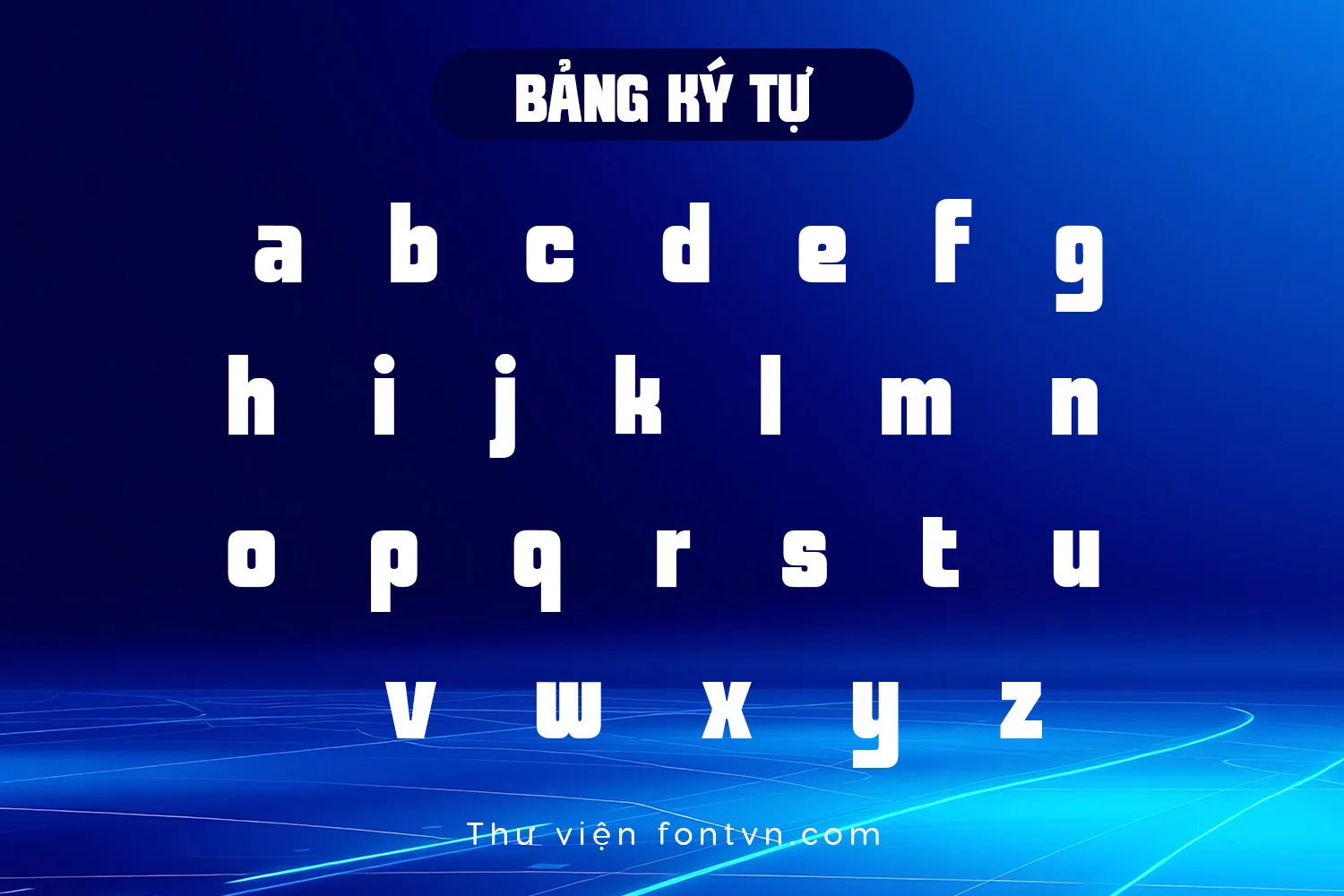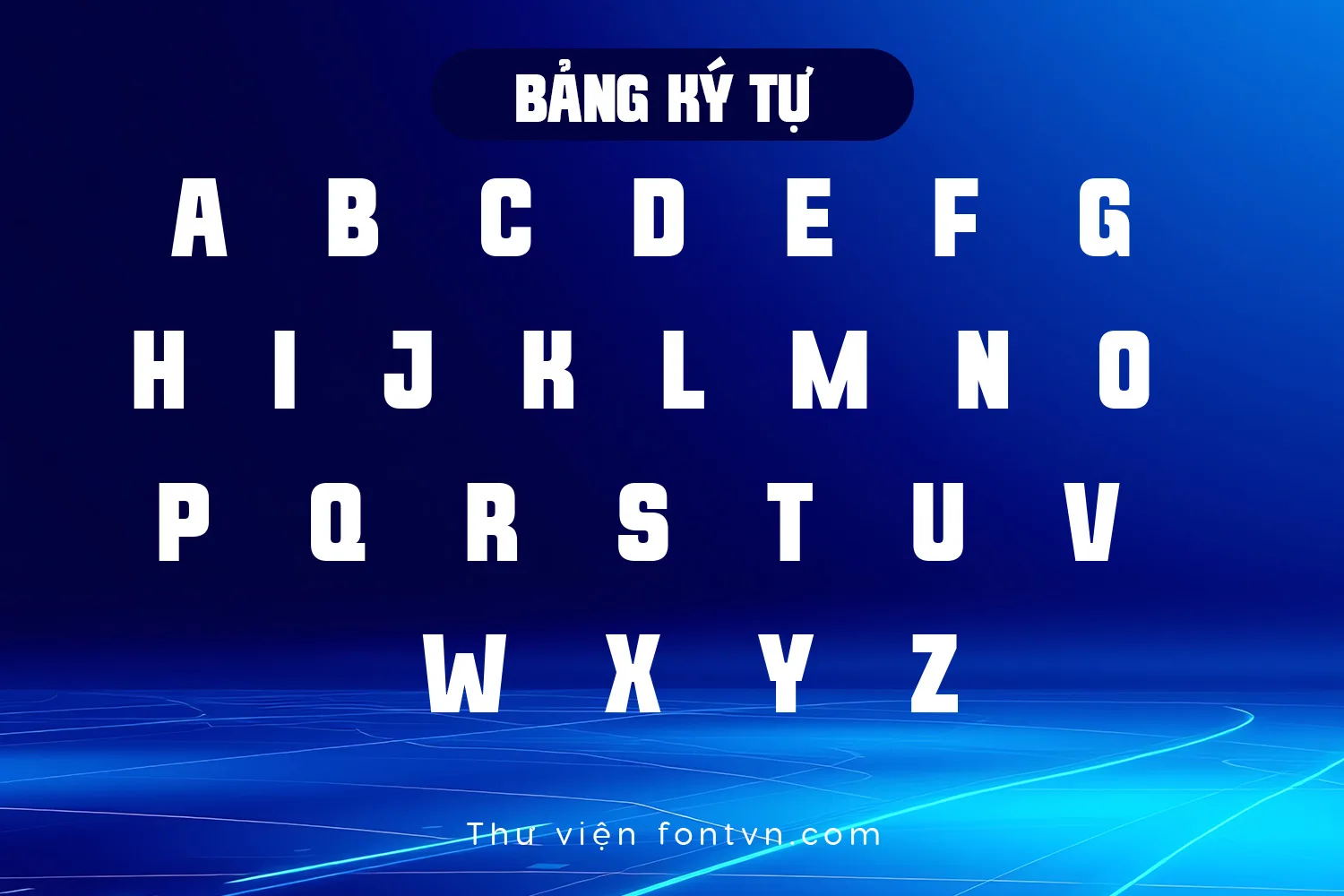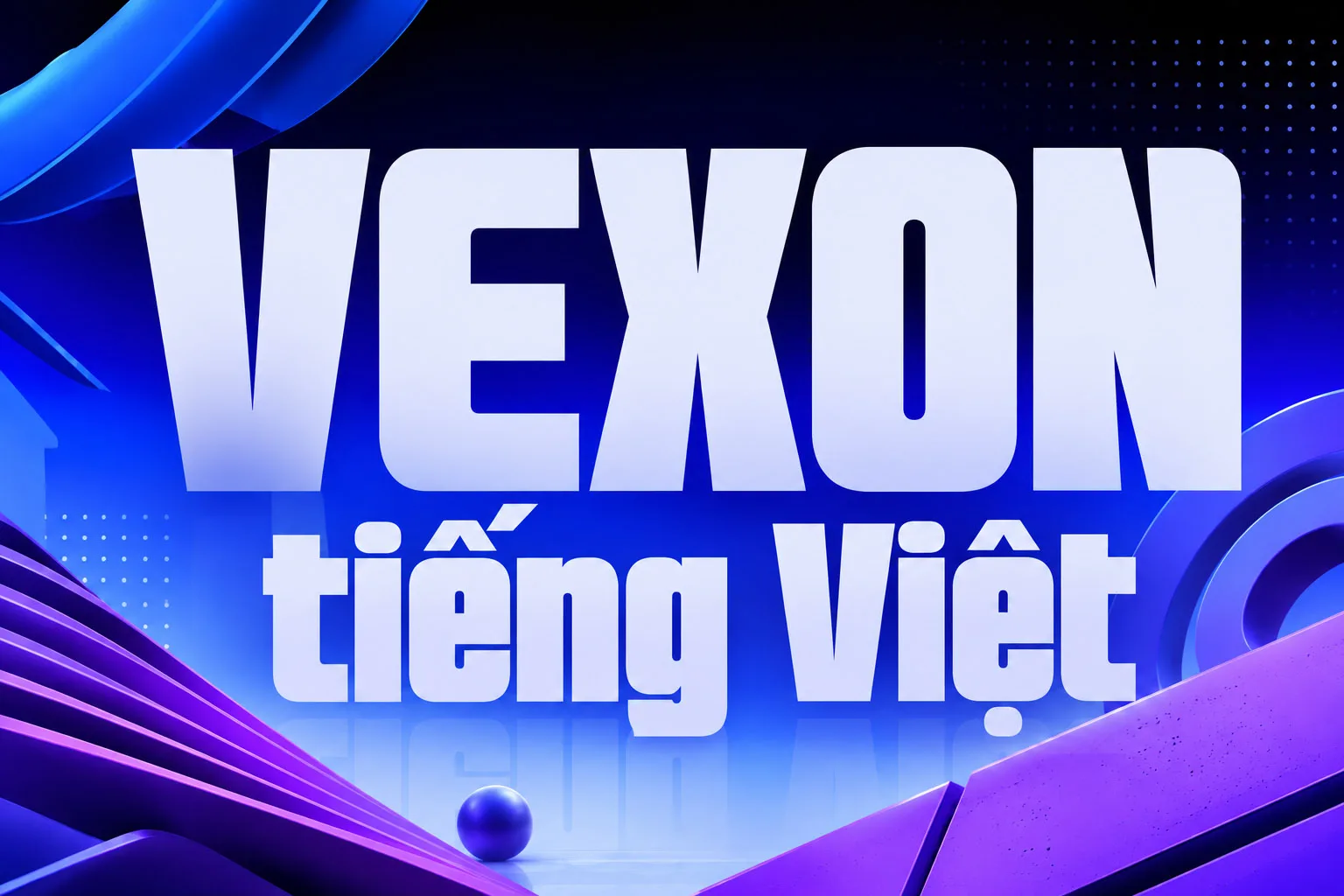
DVN VEXON tiếng Việt – Font Chữ Logo Condensed Hiện Đại, Mạnh Mẽ Dành Cho Branding & Poster
DVN VEXON là font chữ display sans-serif mang phong cách condensed, được thiết kế với những đường nét dày, mạnh mẽ và hình khối hiện đại, giúp tạo nên dấu ấn nổi bật ngay từ cái nhìn đầu tiên. Font phù hợp cho các dự án cần sự ấn tượng, chuyên nghiệp và giàu cá tính.
Với tỷ lệ chữ cao, khoảng cách được tối ưu cùng các góc bo mềm vừa phải, DVN VEXON mang đến khả năng hiển thị rõ ràng ở kích thước lớn, đặc biệt lý tưởng cho thiết kế logo, tiêu đề, poster, banner, bao bì, giao diện game, thể thao điện tử và nhận diện thương hiệu.
Bên cạnh kiểu chữ in hoa mạnh mẽ, font còn được trang bị bộ ký tự mở rộng cùng hỗ trợ tiếng Việt đầy đủ, giúp bạn dễ dàng sử dụng trong các dự án thiết kế dành cho thị trường Việt Nam và quốc tế.